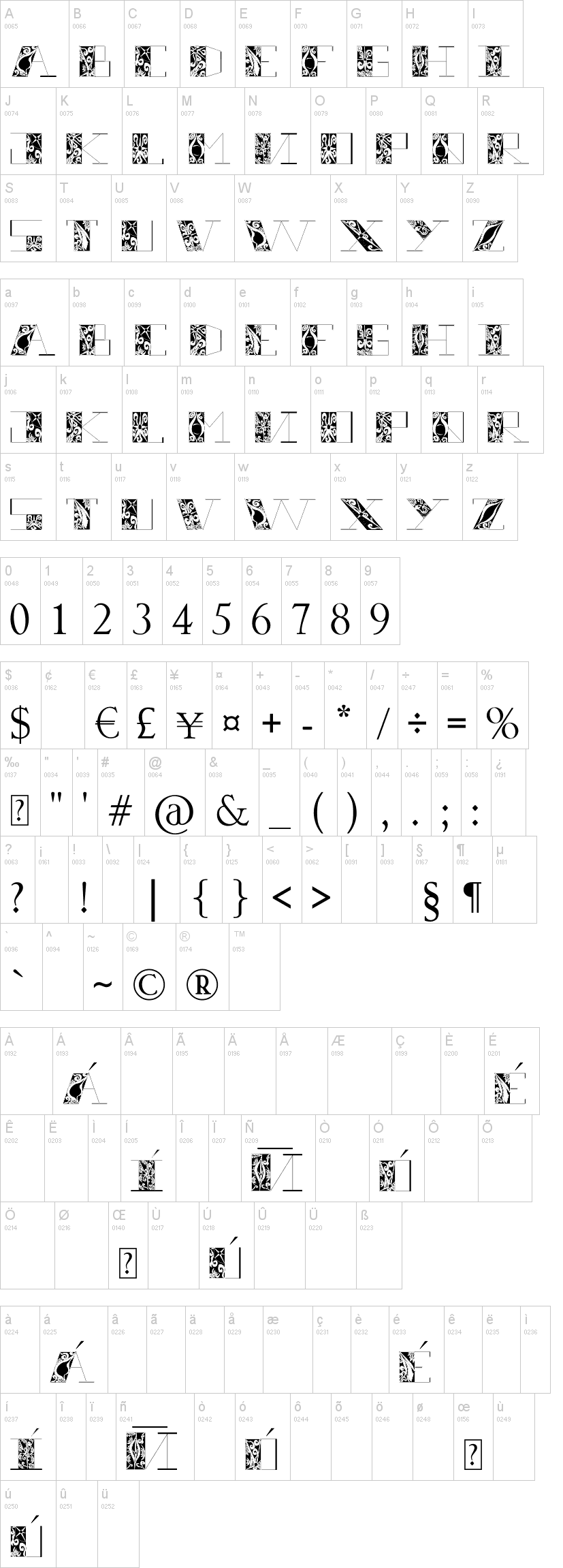
Note of the authorFuente creada a base de la cultura hipster que se encaja en desarrollar y difundir las costumbres vintage que se han generado desde hace mas de 15 años.